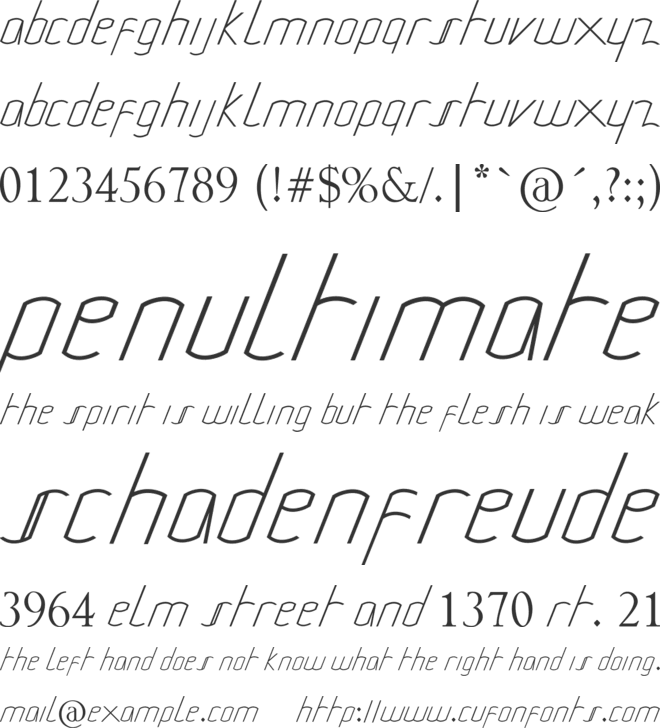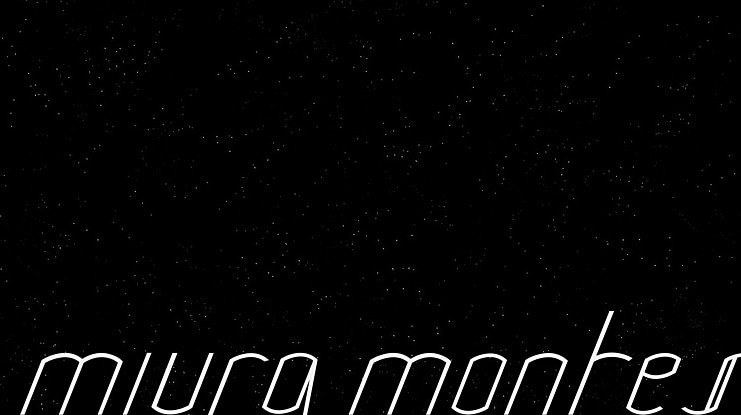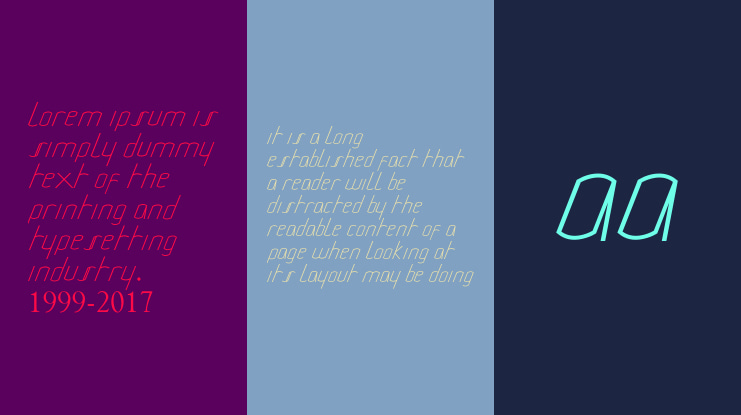
Miura Montes Font
Fuente inspirada en caracteristicas del Lamborghini Miura.
Creada para la Materia Diagramacion y Tipografia de la Universidad Icesi.
Cali - Colombia.